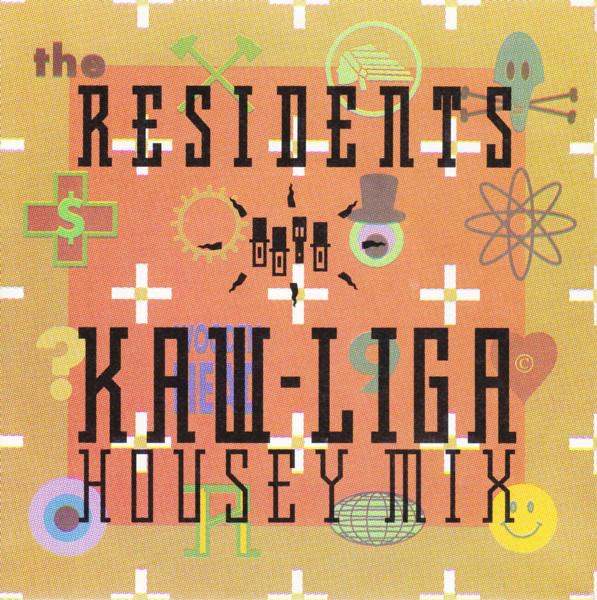
Suche Schrift von diesem Schallplattencover aus den 1980ern (The Residents)
Das Cover ist von 1989 und ich hätte gern gewußt, um welche Schrift es sich dabei handelt. Die Schrift darf auch Premium sein. Auf den üblichen Seiten habe ich nur so ähnliche Fonts gefunden, aber keine mit dem markanten "K" und "W". Danke sehr!
Erinnert mich stark an Schriften von Emigre und Neville Brody – allerdings passt da leider keine wirklich exakt.
Super, Modula Serif passt. Oblong kommt dem Kaw-Liga-Artwork sehr nahe, bis auf das "R" und das "K". Vielleicht wurden einzelne Glyphen editiert? Was ich als Neuling immer wieder mit Erstaunen feststelle: ganz gleich wie aussergewöhnlich eine Schriftart auch anmuten mag, es scheint doch immer wieder auch Schriftarten zu geben, die einander ähneln und sich nur im Detail unterscheiden.